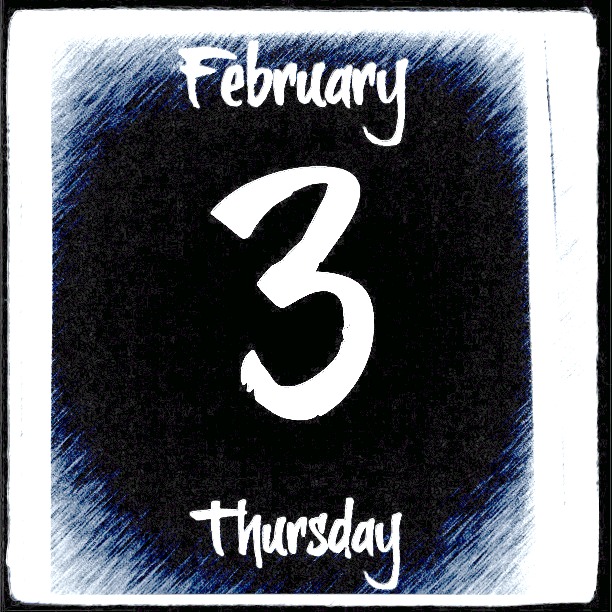
Este jueves el typodarium nos saluda con una fuente caligráfica y una errata, no le hagan caso al typodarium porque su nombre no es brushtipTexe, sino brushtipTerrence. Es una tipografía del holandés Jeroen van der Ham que nos la presenta acompañada de una elocuente cita de Filippo della Strata (1473) “Con un lápiz, el texto es una doncella virtuosa, impreso, se convierte en una prostituta”.
Como si hubiera sido creada con un pincel o brocha -dependiendo del grosor- esta tipografía del 2009 es adecuada para cualquiera que quiera una tipografía con un estilo de declaraciones o reivindicaciones de pared.
Jeroen (nacido en Arnheim en 1971) es una diseñador gráfico, ilustrador y pintor que desarrolla desde el año 2000 principalmente tipografías de tipo manual o caligráficas. Puedes ver su trabajo en la página de su estudio Joebob gráficos en donde nos presenta su trabajo a través de una pizarra mágica… qué tiempos!!!!